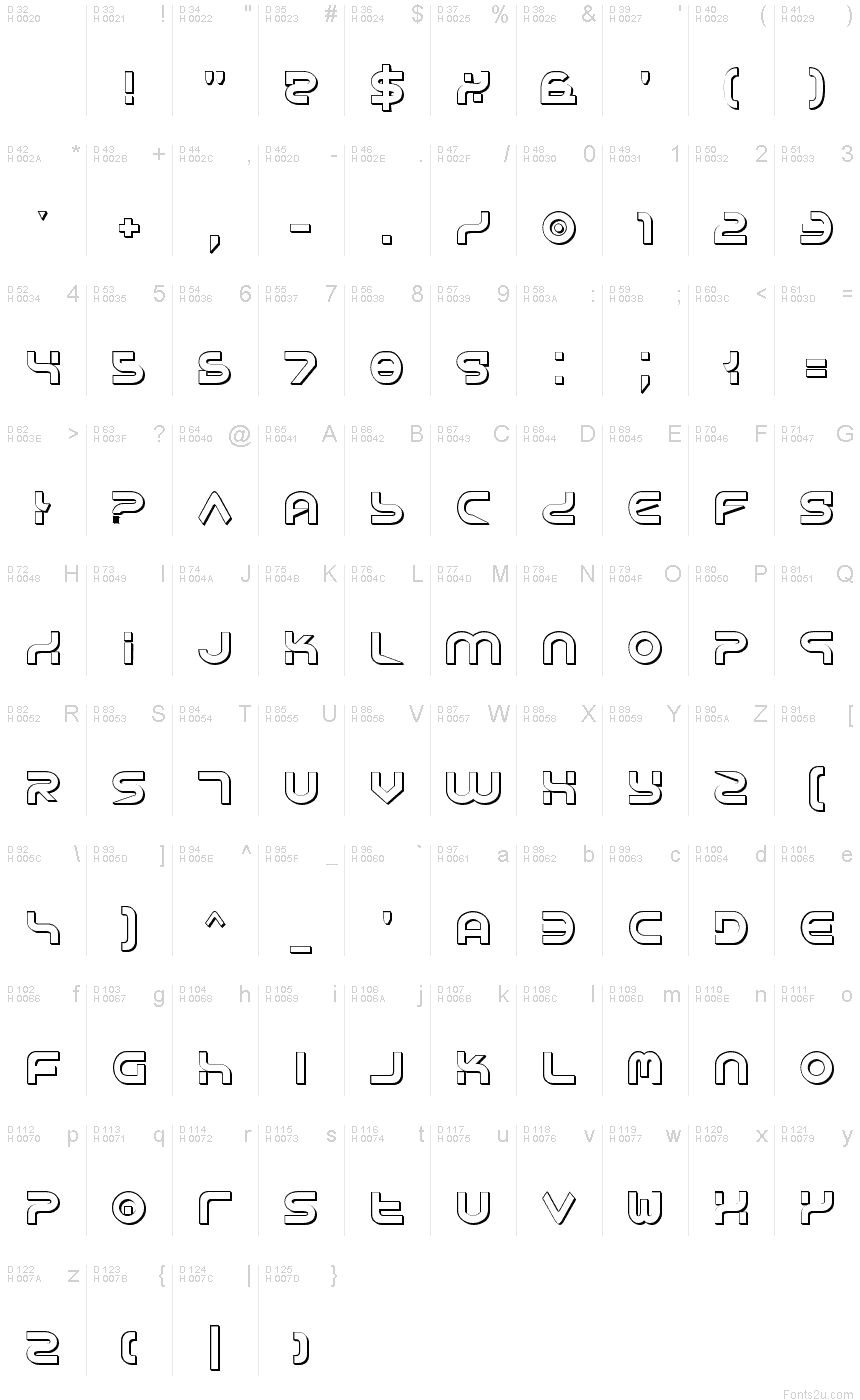
Yukon Tech Shadow, di Iconian Fonts, è un carattere display futuristico e gratuito, con lettere corpose e arrotondate che richiamano lo stile digitale dei primi tempi. Le forme appaiono ampie, levigate e disegnate a macchina, mentre l’ombra offset conferisce al carattere un semplice effetto 3D che mantiene il look nitido, mai eccessivo.
Si adatta perfettamente a poster di fantascienza, loghi di giochi, intestazioni in stile arcade, grafiche per eventi tech e titoli che richiedono una silhouette retro-futuristica audace. Essendo un font gratuito, funziona bene anche per copertine e monogrammi, poiché l’effetto ombra aggiunge profondità senza appesantire le lettere.
Yukon Tech Shadow